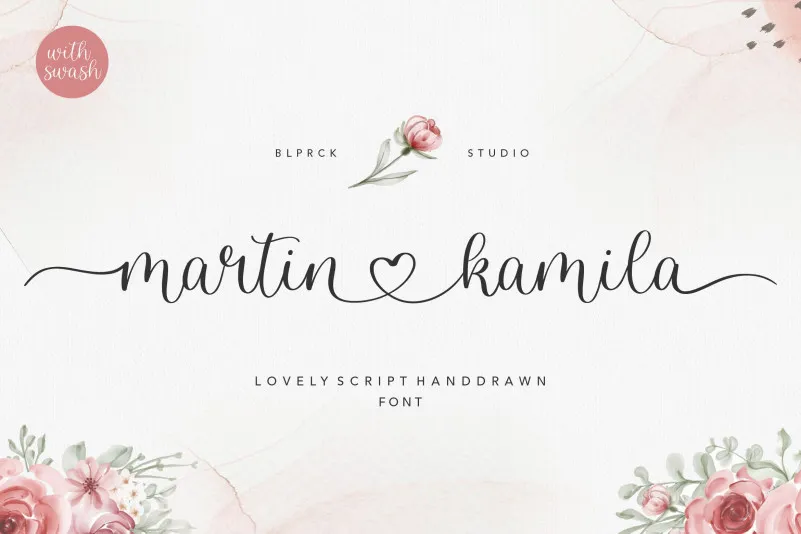
A Martin Kamila Font é perfeita para designers que buscam uma fonte com uma paleta vibrante e versátil para projetos diversos. Com seu design elegante e fluido, essa fonte se destaca especialmente em aplicativos como embalagens de produto, logomarcas, revistas, mídia social, anúncios de casamento ou até mesmo para destacar textos acima de fundos complexos. Suave mas forte ao mesmo tempo, a Martin Kamila oferece uma ótima mistura de estilos, tornando-a um recurso indispensável. Ela combina perfeitamente com qualquer estilo de design gráfico, seja ele minimalista ou extravagante, garantindo sempre um resultado impecável. Com o balpirick como seu criador, você pode se assegurar de uma fonte de alta qualidade e confiabilidade para seus projetos. Seja você um designer gráfico ativo em qualquer segmento da comunicação visual, a Martin Kamila oferece um design único que não deixará os olhos do seu público chocados. Seu uso varia desde criar ambientes de marca incrivelmente unificados e impactantes até decorar páginas de revistas ou anunciar eventos importantes. Esta fonte é uma excelente opção para qualquer designer gráfico, tornando sua missão ainda mais fácil e criativa. Quebre as barreiras do design com a Martin Kamila Font.